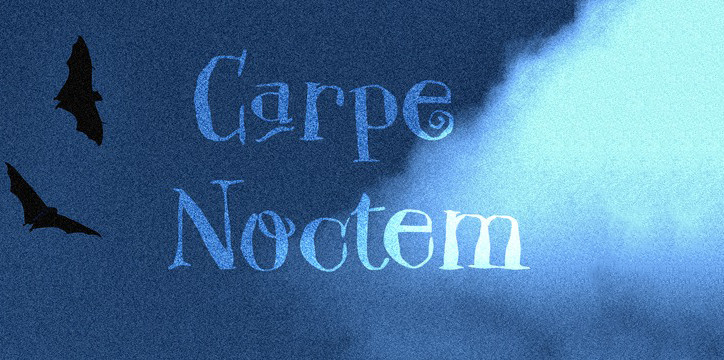
Carpe Noctem é uma nova adição à família dos Hanoded fonts, criada pelo talentoso designer Hamilton. Essa serif typeface oferece algo que vai além da mera sobriedade habitual: um ar de aterrorizante encantamento e elementos intrincados que fizeram parte do folclore medieval. Carpe Noctem tem as linhas anguladas e os detalhes em forma de volta que você está procurando, especialmente se deseja dar um toque misterioso ou assustador aos seus projetos de design. Além disso, a typeface apresenta alternativas para alguns dos caracteres mais curvados do sistema original, proporcionando ainda mais flexibilidade e personalização. Para completar o estilo medieval, a fonte também inclui uma versão alternativa da famosa marcação “ampersand”, trazendo à vida um pouco de magia do mundo ocidental em cada letra. Se estiver procurando por algo que dê ao seu design aquela nota especial e única, Carpe Noctem é definitivamente o tipo certo para você.